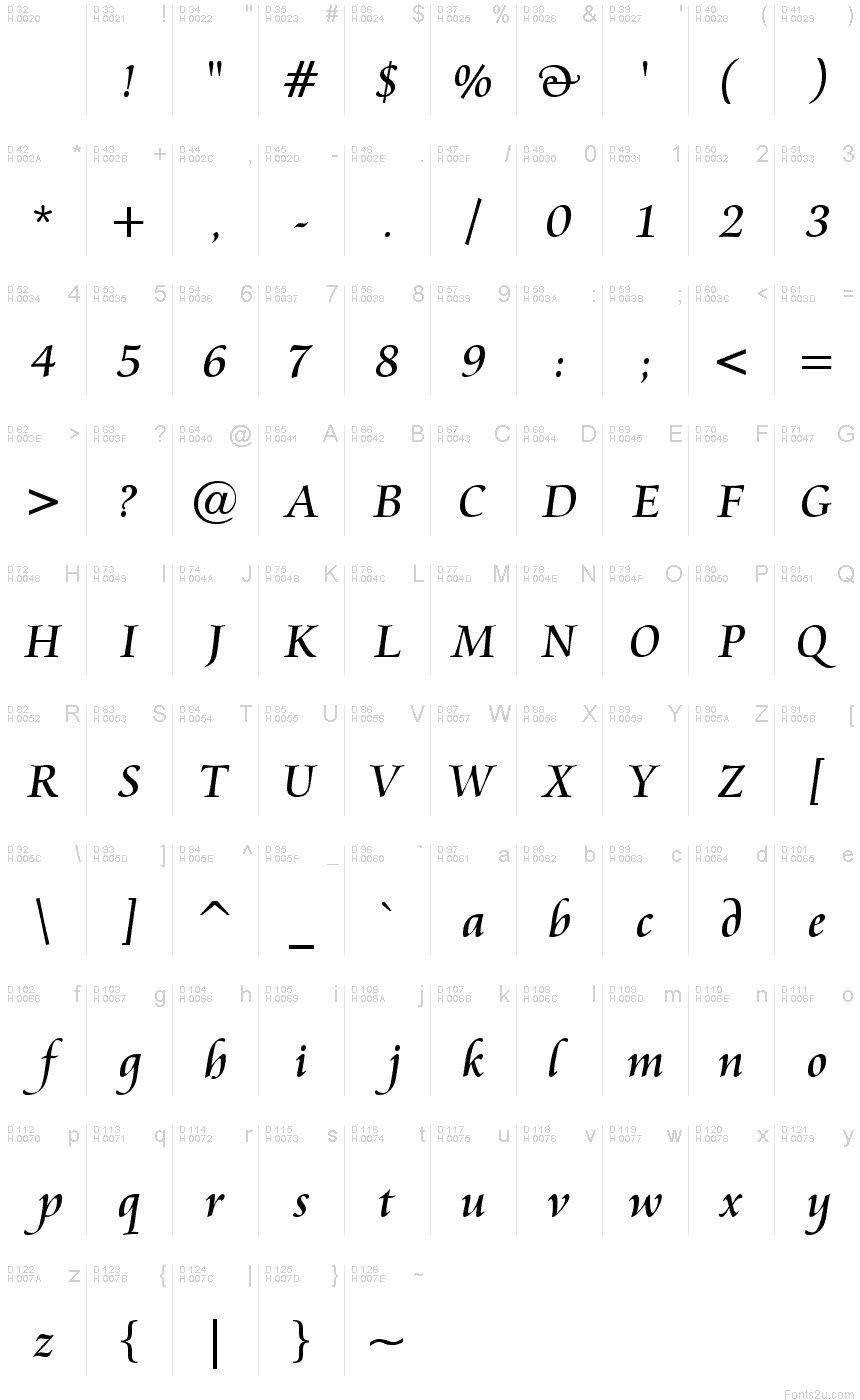
Tonite
Tonite to darmowy, pochyły krój szeryfowy o delikatnej elegancji wieczornej prasy. Litery pochylają się w szybkim, płynnym rytmie, łącząc ostre, klinowe szeryfy i wysoki kontrast z detalami w kształcie łezek, co nadaje krojowi lekko kaligraficzny i nostalgiczny wyraz.
Idealnie pasuje do okładek magazynów, tytułów filmowych, identyfikacji wizualnych restauracji, obwolut książek oraz zaproszeń na wydarzenia czy pokazy mody, gdzie krótki tekst potrzebuje odrobiny szyku i dynamiki. Jako darmowy krój, Tonite sprawdza się najlepiej, gdy pozwolisz tym płynnym kursywom przejąć główną rolę w krótkich nagłówkach, nazwiskach i innych kompaktowych projektach.